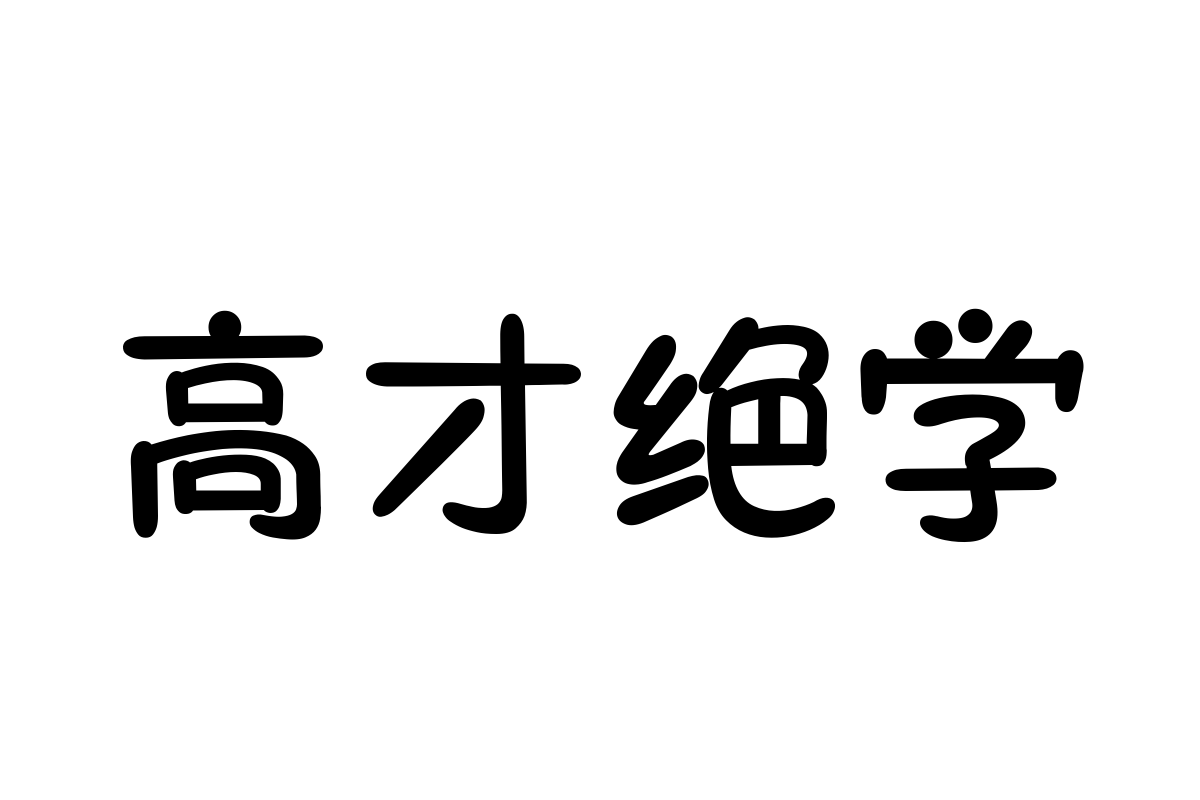
汉仪橡皮泥是一款专业的字体软件,它提供了多种中文字体供用户选择。这些字体包括了宋体、黑体、楷体、仿宋等常用字体,以及一些特殊效果的字体如粗体、斜体、装饰字等。
汉仪橡皮泥的字体设计非常精美,线条流畅,字形清晰,非常适合用于各种印刷品和电子屏幕上。同时,这款字体还支持自定义字体,用户可以根据自己的需求调整字体的大小、颜色、粗细等参数,以达到最佳的视觉效果。